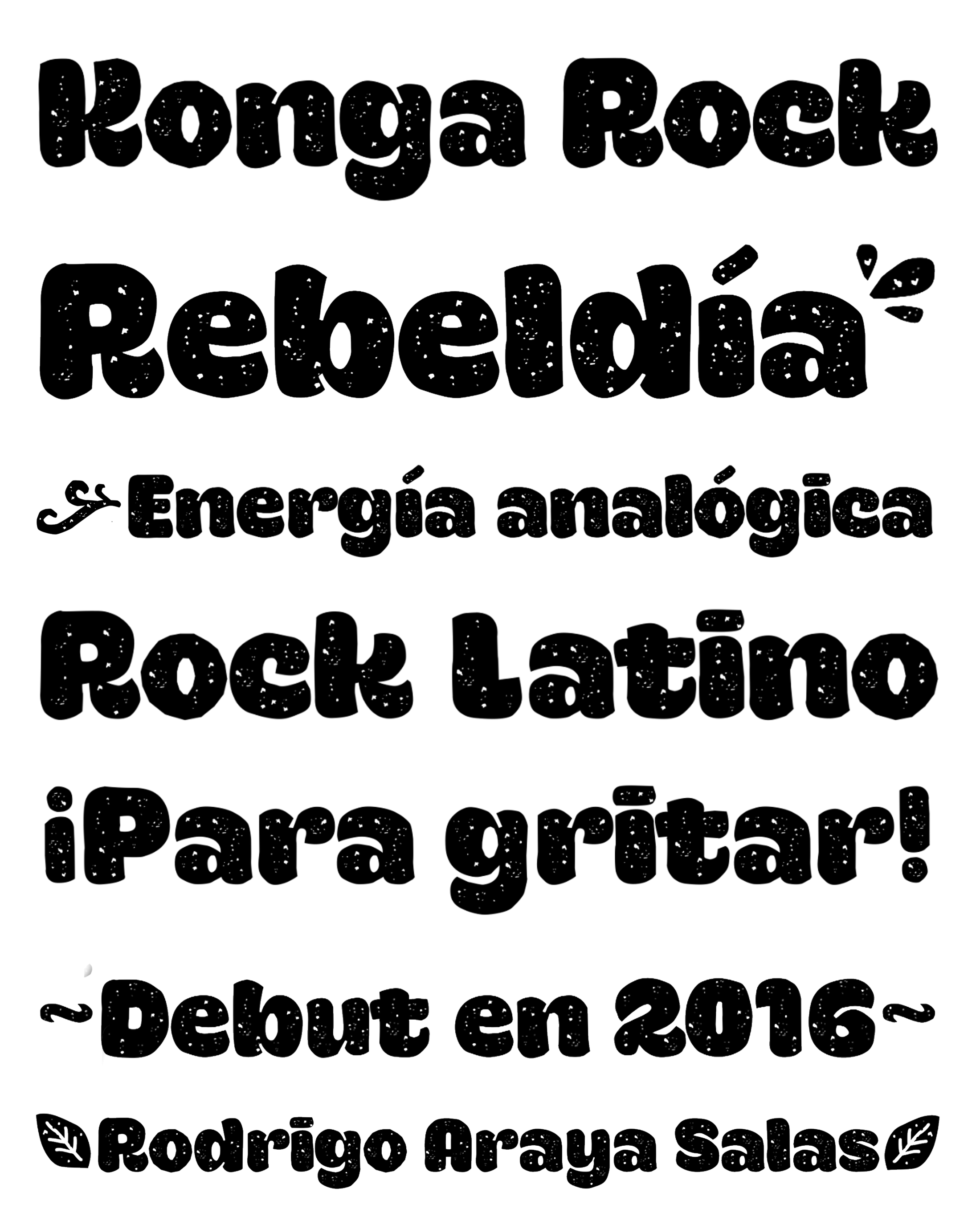
Konga Rock
| Año | 2016 |
| Créditos | Rodrigo Araya Salas |
| Descripción | La familia tipográfica Konga Rock fue diseñada por Rodrigo Araya Salas y publicada por RodrigoTypo. Konga Rock contiene 2 estilos. Es un nuevo estilo de Konga Pro, ahora más tosco y con más adornos. |
| Clasificación | Títulos, Dingbats |
| Familia(s) | Konga Rock, Konga Rock Ornament |
| Estilos | 2 |
| Fundidora | RodrigoTypo |